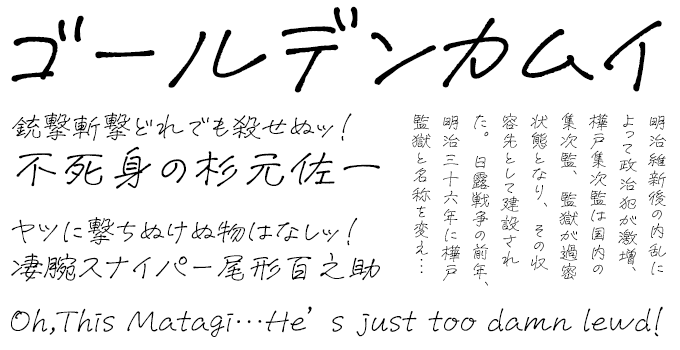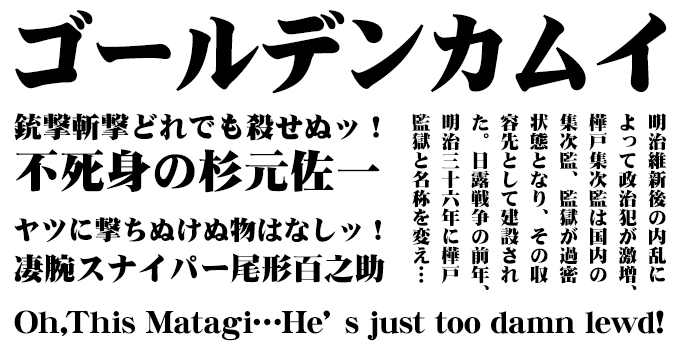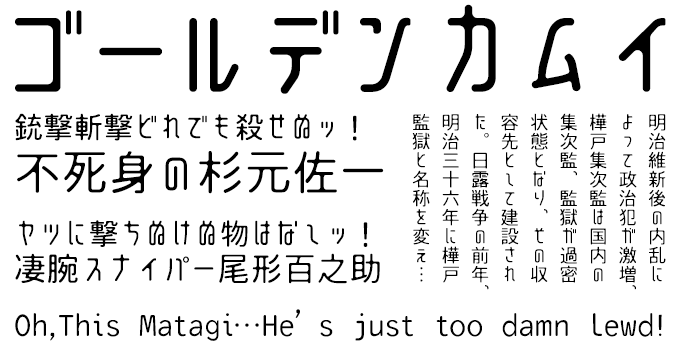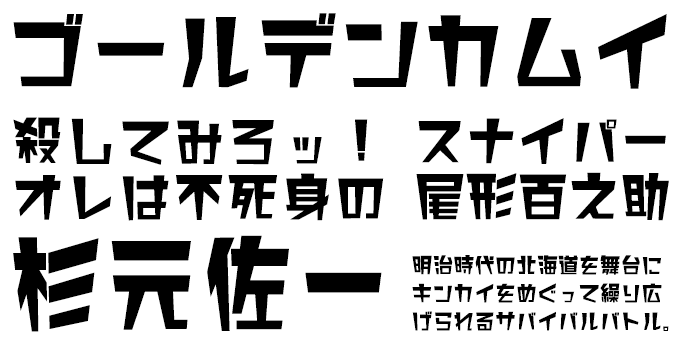
「ゴールデンカムイ」に合うフォント:特化型 目的別フォントガイド #127
今回は「ゴールデンカムイ」に合うフォント。日々フォントのことばかり考えている当店スタッフが直感的に選んだフォントをご紹介します。
「ゴールデンカムイ」に合うフォントをスタッフが選びました
「ゴールデンカムイ」に合うフォント DFひびゴシック体 W14
ひびの入った無骨なイメージの書体
▶DFひびゴシック体 W14【ダイナフォント】
「ゴールデンカムイ」に合うフォント AFCoffee3
超極太ゴシック体をベースに、筆画の一部に切り込みを入れることでまばらな印象にデザインされた書体。ゴールデンカムイのイメージに合うひびの入った力強いフォントです。
「ゴールデンカムイ」に合うフォント 東亜重工 GRUNGE
グランジ加工が厳しい旅を彷彿とさせる
▶東亜重工 GRUNGE【イワタ書体ライブラリー】
「ゴールデンカムイ」に合うフォント 東亜重工 GRUNGE
東亜重工製フォント『東亜重工』にグランジ(汚れ)加工を施したフォントです。骨ばったデザインが厳しい旅と戦いを彩ります。
「ゴールデンカムイ」に合うフォント 明治教科書明朝
ゴールデンカムイの世界観によく合う明朝体
▶明治教科書明朝【フォントグラフィック】
「ゴールデンカムイ」に合うフォント 明治教科書明朝
明治期の教科書活字を基本に忠実にレタリングしました。
「ゴールデンカムイ」に合うフォント 筑紫アンティーク明朝
古く美しい明朝体
▶筑紫アンティーク明朝【フォントワークス】
「ゴールデンカムイ」に合うフォント 筑紫アンティーク明朝
漢字そのものが持っている形の美しさをそのままに、金属活字時代のインクが濃く香り立つページに遭遇した時のような風情の明朝体です。
「ゴールデンカムイ」に合うフォント 筑紫ゴシック
オーソドックスなゴシック体
▶筑紫ゴシック【フォントワークス】
「ゴールデンカムイ」に合うフォント 筑紫ゴシック
モダンなシャープさやクリーンな硬質さを備えた部分とクラシックな味わいや柔らかな部分を融合させており、オーソドックスでありながらも見る人に新鮮さを与えることができます。
「ゴールデンカムイ」に合うフォント 闘龍書体
様々なアニメ作品で使用される人気の毛筆書体
▶闘龍書体【昭和書体/コーエーサインワークス】
「ゴールデンカムイ」に合うフォント 闘龍書体
コミックの販促ポスターなどに度々使用された毛筆書体。闘争心にあふれ、力がありあまった若い龍が、空を舞うさまをイメージして作られた筆書系デザイン書体です。拡大して使うほどに迫力が増す「かすれ」を存分に活かした、昭和書体を代表する人気書体です。
「ゴールデンカムイ」に合うフォント DSストロング
無骨な角ばったデザインが金カムタイトルっぽいデザイン書体
▶DSストロング【七種泰史/デザインシグナル】
「ゴールデンカムイ」に合うフォント DSストロング
ゴールデンカムイのタイトルロゴ風の角ばったデザインフォント。見出しやキャッチコピーにぴったり。岩石のような堅さ、力強さの中にも優しさを感じる、太く元気な書体です。
「ゴールデンカムイ」に合うフォント DF龍門石碑体 W9
無造型に彫ったような字形と線質がアイヌ彫刻をイメージさせる書体
▶DF龍門石碑体 W9【ダイナフォント】
「ゴールデンカムイ」に合うフォント DF龍門石碑体 W9
アイヌ工芸に見られる大胆で力強い彫りのイメージに合うフォント。その龍門の書体様式と特長を持った書体です。無造型に彫ったような字形と線質は、細かいことに拘泥しない強い雰囲気をたたえています。
「ゴールデンカムイ」に合うフォント 花とちょうちょ
アイヌ語で花は「ノンノ」ちょうちょは「マレウレウ」
▶花とちょうちょ 【鈴木メモ】
「ゴールデンカムイ」に合うフォント 花とちょうちょ
鈴木メモの「花とちょうちょ」は、そのまま打ち込むだけでめちゃめちゃ暖かくて可愛いくてサマになる手書きフォントです。
「ゴールデンカムイ」に合うフォント 空とひこうき
アイヌは自らの言葉を文字に記すこともなかったが、文字化するなら「空とひこうき」が合う
▶空とひこうき【鈴木メモ】
「ゴールデンカムイ」に合うフォント 空とひこうき
インクのようなにじみを生かしたラフなデザインで、どんな事柄にも相性抜群!邪魔しないけど主張する手書きフォントです。
「ゴールデンカムイ」に合うフォント 京円
アニメの本編で使用される純和風毛筆書体
▶京円【白舟書体】
「ゴールデンカムイ」に合うフォント 京円
アニメの本編の次回予告などで使用されていた毛筆書体。墨のにじみを生かした、円やかで上品な京の薫りのする書体、純和風という言葉にピッタリな書体です。
「ゴールデンカムイ」に合うフォント モトヤ刀筆6
刀をイメージしたアクセントがアイヌの木彫りをイメージさせる書体
▶モトヤ刀筆6【モトヤ】
「ゴールデンカムイ」に合うフォント モトヤ刀筆6
アイヌ工芸に見られる大胆で力強い彫りのイメージに合うフォント。「爨宝子碑(さんぽうしひ)」という書の古典を基に制作され、ゴシック体の骨格に刀をイメージしたアクセントを付与し、鋭さや躍動感、伝統的な品格を表現した書体です。
「ゴールデンカムイ」に合うフォント HG創英イオリ書体
アイヌに文字はないけれど、あったらこんな感じ?
▶HG創英イオリ書体【リコー】
「ゴールデンカムイ」に合うフォント HG創英イオリ書体
力強くも温かみのある極太フォント。アイヌの荒々しさも表現できます。
「ゴールデンカムイ」に合うフォント DF超極太明朝体
金カムをイメージさせる極太で力強いオールドスタイルの明朝体
▶DF超極太明朝体【ダイナフォント】
「ゴールデンカムイ」に合うフォント DF超極太明朝体
ゴールデンカムイのテーマが持つ力強さを表現できる明朝体。華康明朝体をベースに開発され、通常のストロークの曲線や仮名の連画を増やし、横画においても三角形部分の円弧をより滑らかにデザインする事で、伝統的な書道の美しさを追求した明朝体になっています。
「ゴールデンカムイ」に合うフォント KOくれたけ銘石B
彫刻の味わいが加えられた隷書体がアイヌの力強さをイメージさせます
▶KOくれたけ銘石B【欣喜堂】
「ゴールデンカムイ」に合うフォント KOくれたけ銘石B
アイヌ工芸に見られる大胆で力強い彫りのイメージに合うフォント。中国・晋代の『王興之墓誌』にみる、彫刻の味わいが加えられた隷書体の一種、とくに「銘石体」と呼ばれる書風がベースになっています。自然なゆらぎやゆがみのある直線で構成された、強い風格でありながらも目に優しいゴシック体です。
「ゴールデンカムイ」に合うフォント ヒラギノ角ゴオールド W9
金カムをイメージさせる極太で力強いオールドスタイルのゴシック体
▶ヒラギノ角ゴオールド W9【ヒラギノフォント】
「ゴールデンカムイ」に合うフォント ヒラギノ角ゴオールド W9
ゴールデンカムイのテーマが持つ力強さを表現できるゴシック体。昭和初期の金属活字をベースに作られた仮名書体にヒラギノ角ゴの漢字・欧文を組み合わせたゴシック体。
「ゴールデンカムイ」に合うフォント  FGPミライゴシック
レトロと未来的な要素がミックスした不思議な書体
▶FGPミライゴシック【フォントグラフィック】
「ゴールデンカムイ」に合うフォント FGPミライゴシック
明治末期を舞台とした内容が現在人気なアニメには未来的イメージなフォントが似合います。